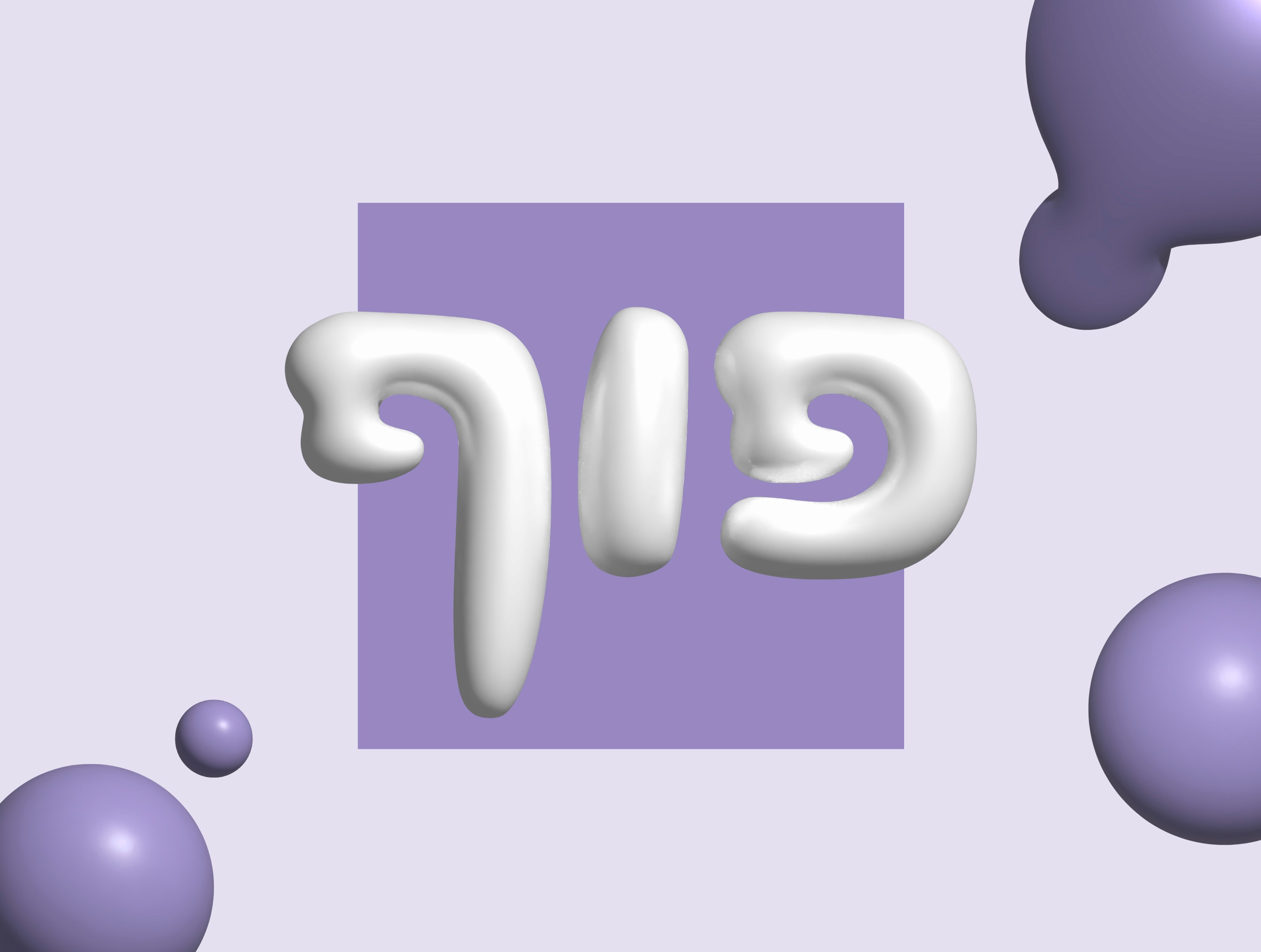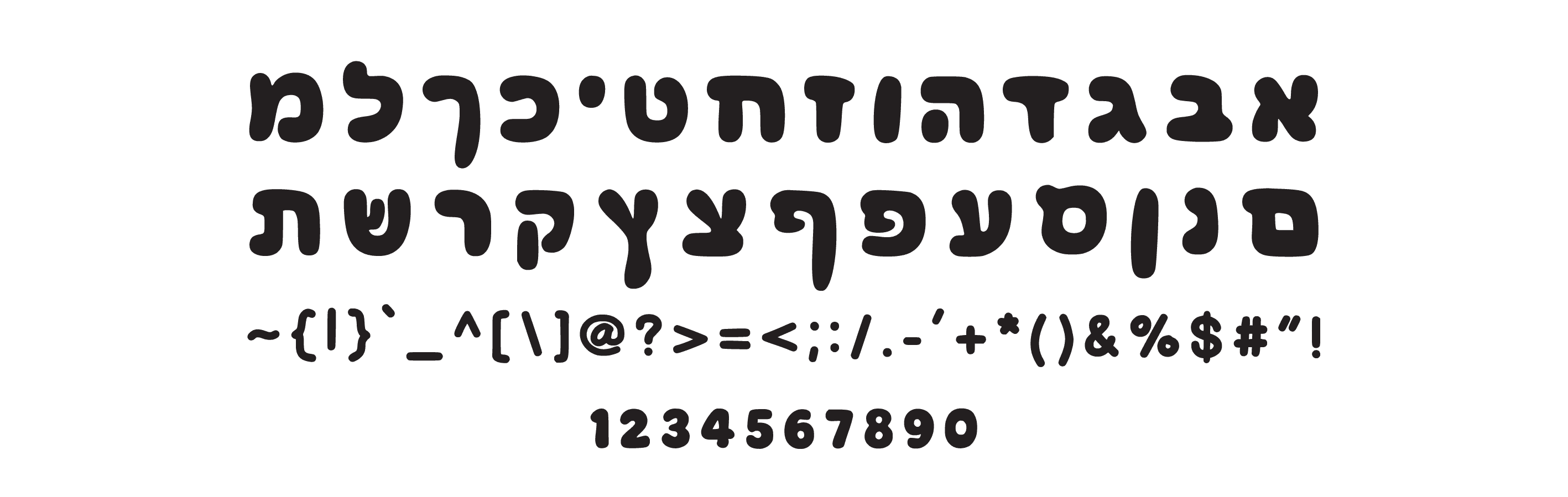
פונט פוף
פונט עברי עגול, נפוח וכיפי, מושלם ללוגואים, פוסטרים ומיתוג צבעוני ושמח.
פוף — פונט שאפשר כמעט לנשוך
עגלגל, שמנמן, מבריק ונעים — פונט פוף נכנס לעיצוב כמו בלון מתוק.
כל אות נראית כמו בועת גומי רכה, עם קווים עבים ועגלגלים שמביאים איתם אנרגיה של כיף וקלילות.
הוא מתאים בדיוק לעיצובים שמבקשים למשוך עין, לשדר רכות ילדותית, או להכניס הומור קליל לעיצוב — כמו צעצועים, ממתקים, פוסטרים צבעוניים ולוגואים שובבים.
איפה הוא מרגיש בבית?
🍬 לוגואים של ממתקים ומוצרים לילדים
🎈 פוסטרים לפסטיבלים, מסיבות וחגים
🪄 עיצובים צבעוניים ושמחים
🎨 מיתוג קליל בעולמות של צעצועים, עיצובי POP או גרפיקה הומוריסטיתלמי הוא מתאים?
למעצבים שמחפשים פונט מלא חיות, למותגים צעירים או למי שרוצה ליצור אווירה רכה, עגלגלה ומחויכת.הורידו עכשיו ותנו לטקסטים שלכם מראה עגול, חמים ונפוח — בדיוק כמו פוף.